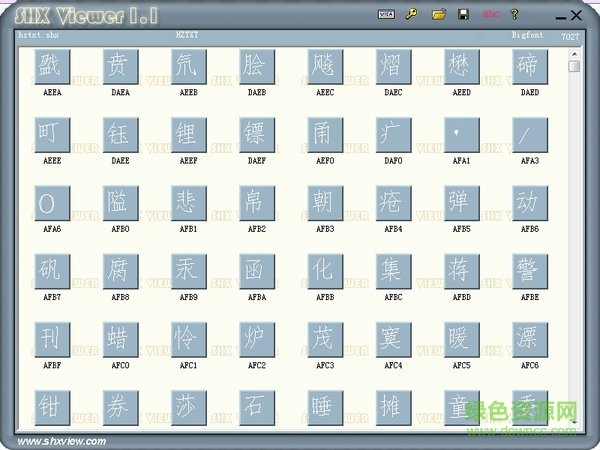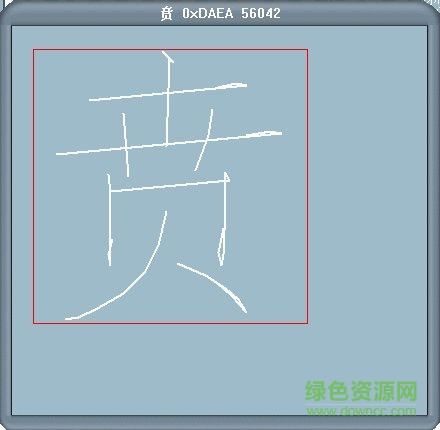
cad findhztxt.shx字體
findhztxt.shxautocad中的一款設(shè)計(jì)字體,是單線仿宋體的cad字體格式,而部分用戶將其該名稱findhztxt.shx,使得這款字體無法顯示,所有大家在找的findhztxt.shx字體實(shí)質(zhì)上就是hztxt.shx字體,快來綠色資源網(wǎng)試試吧!
findhztxt.shx字體特說明
hztxt.shx字體為單線矢量仿宋體,是最有用的cad字體,主要作用是:顯示CAD圖紙中的中文漢字。
仿宋體介紹
仿宋體是一種采用宋體結(jié)構(gòu)、楷書筆畫的較為清秀挺拔的字體,筆畫橫豎粗細(xì)均勻,常用于排印副標(biāo)題、詩詞短文、批注、引文等,在一些讀物中也用來排印正文部分。
仿宋體的書寫比宋體和黑體都方便快捷,因?yàn)橹灰?jì)算好字格就可以用鋼筆或毛筆(需用較硬的狼毫筆)直接書寫。另一方面,仿宋體注重結(jié)構(gòu)造型,與楷書比較接近,多練習(xí)仿宋體有利于準(zhǔn)確地掌握漢字的基本結(jié)構(gòu),在此基礎(chǔ)上再學(xué)習(xí)其它美術(shù)字體就更為方便快速。